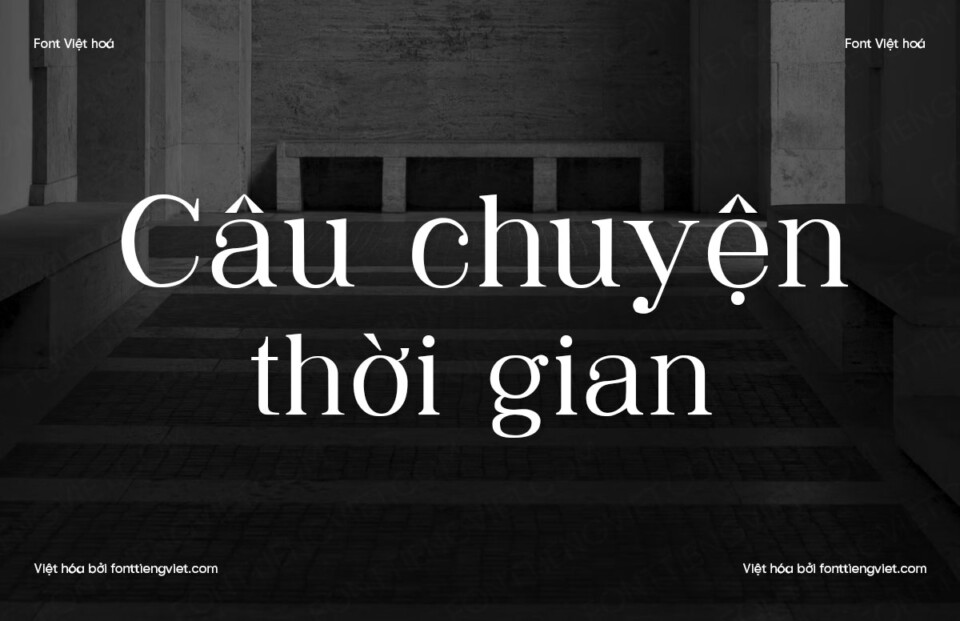
Tải Ngay Font Việt hóa 1FTV VIP Qylen – Bộ Font Chữ Hoàn Hảo Cho Học ĐườngGiới thiệu bộ Font Việt hóa 1FTV VIP Qylen độc đáoTrong các hoạt động giáo dục, việc lựa chọn một Font Miễn Phí và đẹp mắt đóng vai trò rất quan trọng để thu hút sự chú ý của học sinh. Bộ Font Việt hóa 1FTV VIP Qylen chính là giải pháp hoàn hảo đáp ứng đầy đủ các tiêu chí về thẩm mỹ và tính ứng dụng cao. Được thiết kế với các đường nét hiện đại, tinh tế nhưng không kém phần gần gũi, phông chữ này giúp mọi bài giảng trở nên sinh động và chuyên nghiệp hơn.Ưu điểm nổi bật của Font Việt hóa 1FTV VIP Qylen trong dạy họcHỗ trợ tiếng Việt trọn vẹn và hiển thị rõ nétĐiểm cộng lớn nhất của Font Việt hóa 1FTV VIP Qylen là khả năng hiển thị tiếng Việt cực chuẩn, hoàn toàn không xảy ra lỗi dấu hay phân tách ký tự. Điều này giúp các thầy cô giáo dễ dàng soạn thảo giáo án, bài giảng điện tử PowerPoint một cách nhanh chóng. Phông chữ có độ tương phản tốt, giúp học sinh dễ dàng đọc chữ từ khoảng cách xa mà không bị mỏi mắt.Ứng dụng đa dạng cho các dự án trường họcKhông chỉ dùng cho bài giảng, bạn còn có thể ứng dụng bộ phông chữ này vào việc thiết kế báo tường, áp phích sự kiện, thiệp mời hay các tài liệu học tập phát tay. Sự linh hoạt trong kiểu dáng giúp sản phẩm thiết kế luôn giữ được sự nghiêm túc của môi trường sư phạm nhưng vẫn mang lại cảm giác sáng tạo, mới mẻ.Kết luận và hướng dẫn tải font chữ bản quyền miễn phíViệc nâng cao chất lượng thị giác cho bài giảng bằng những phông chữ đẹp mắt như Font Việt hóa 1FTV VIP Qylen sẽ mang lại hiệu quả tiếp thu kiến thức tốt hơn cho các em học sinh. Hãy nhanh tay truy cập Font Miễn Phí, Font Việt Hóa, Font Việt hóa 1FTV VIP Qylen để sở hữu ngay bộ gõ tuyệt vời này cho các dự án giáo dục sắp tới của mình.
Font Việt hóa 1FTV VIP Qylen